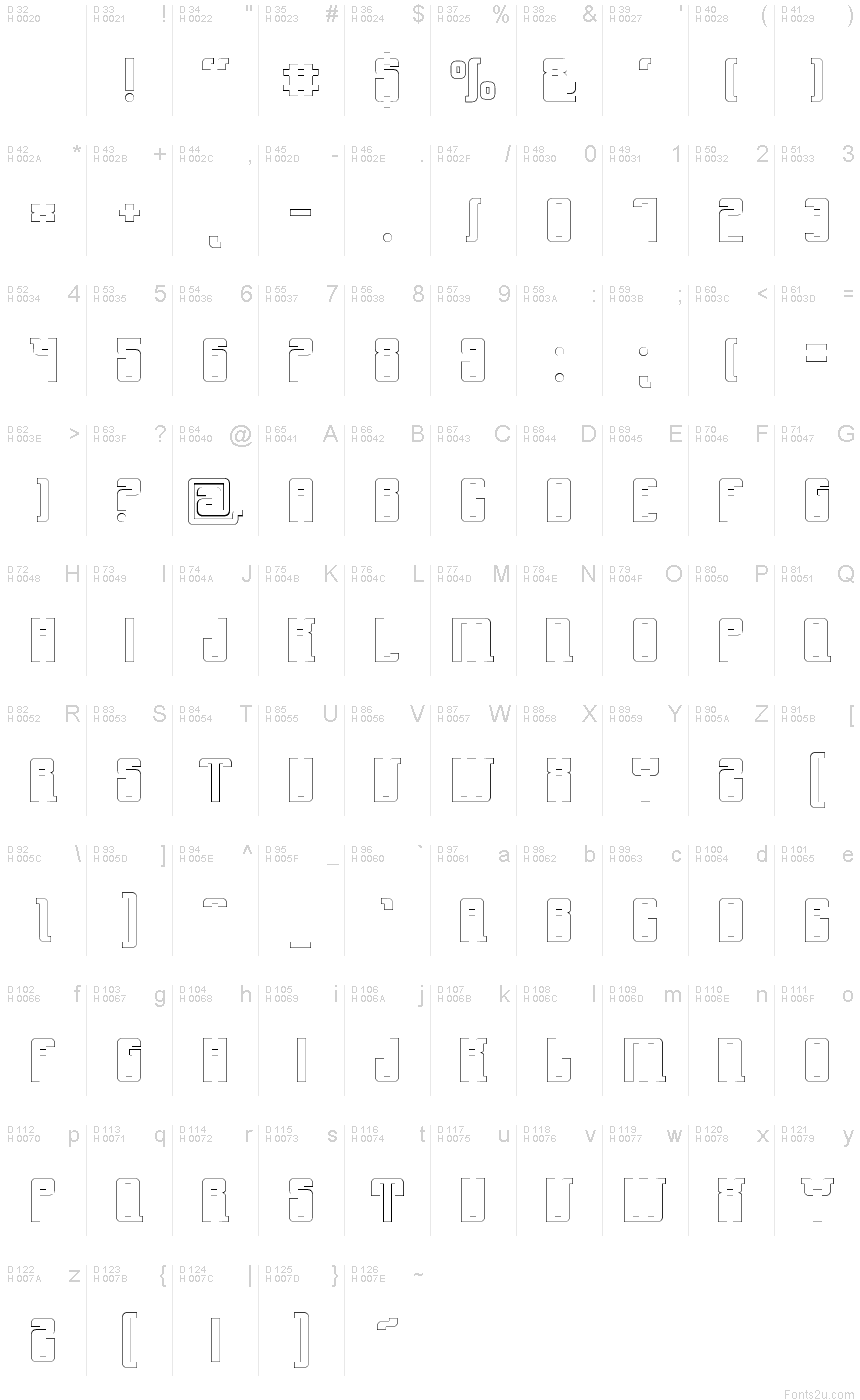
YnduOut od Barmee je bezplatné moderní display písmo s technickým nádechem konce 20. století. Velká písmena jsou vysoká, zaoblená a hranatá, s velkorysými vnitřními otvory a jednoduchým obrysem, díky kterému působí znaky vzdušně, i když jsou tvary pevné a kompaktní.
Skvěle se hodí na plakáty, klubové letáky, herní tituly, obaly hudebních nosičů nebo krátké logotypy, kde vynikne jeho trubková geometrie. Jako bezplatný font se také hodí pro titulní karty, nadpisy a monogramy, zejména pokud hledáte čistý obrysový vzhled, který působí futuristicky, aniž by byl příliš uhlazený nebo ostrý.